Что такое кернинг и как он влияет на восприятие текста
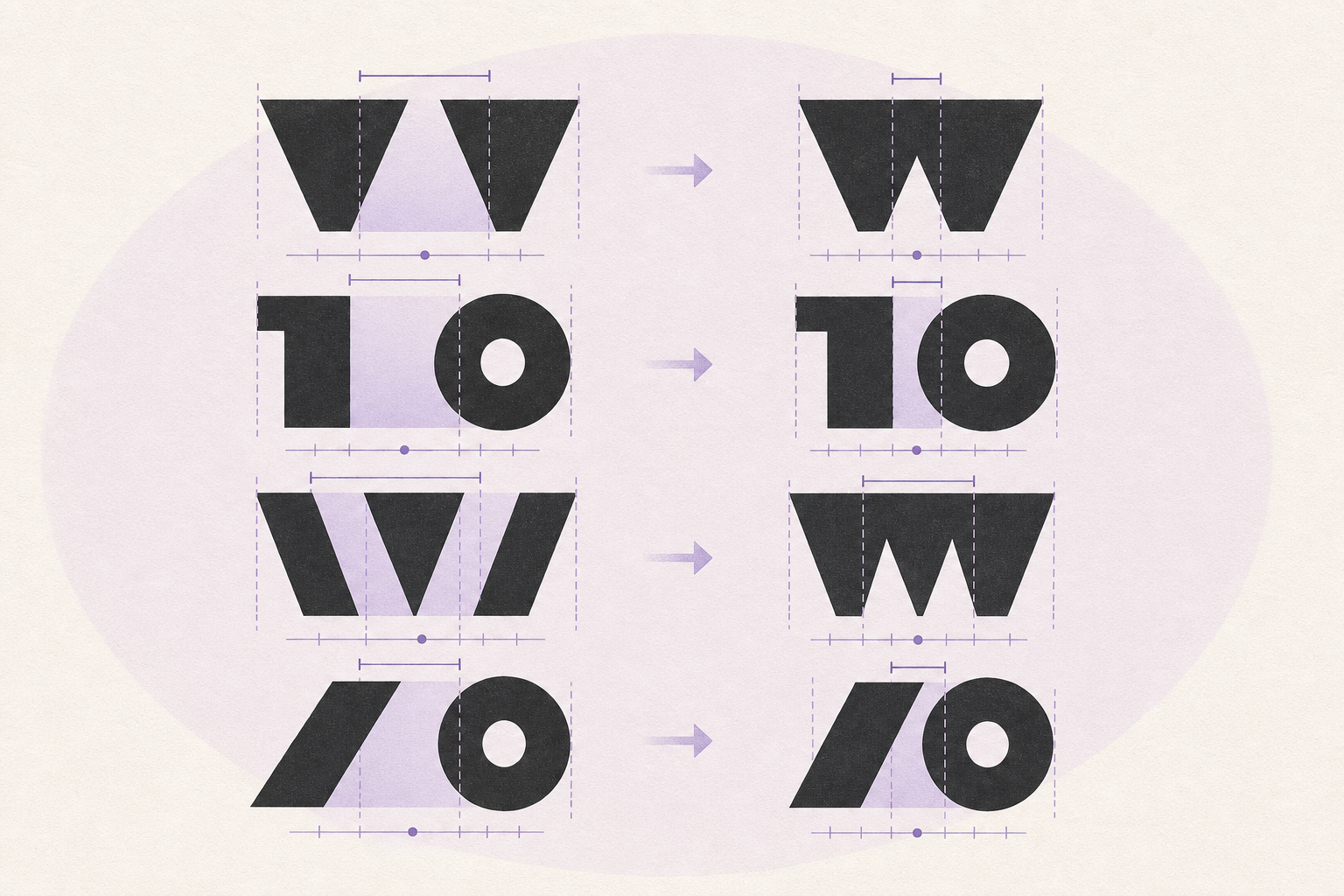
Кернинг — это настройка расстояния между конкретными парами букв, которая помогает визуально выровнять слово и сделать текст цельным. Он особенно заметен в логотипах, заголовках и крупных надписях, где даже небольшой дисбаланс меняет ритм композиции. Ниже разберём принципы кернинга, практические приёмы, ошибки и способы проверки.
Кернинг: простое определение термина
В типографике кернингом называют изменение бокового интервала между двумя определёнными символами. Цель не в том, чтобы сделать все буквы одинаково близкими, а в том, чтобы расстояния между их визуальными массами воспринимались равномерно. Поэтому кернинг часто выполняется не по геометрической линейке, а оптически — с учётом формы знаков.
Например, рядом стоящие латинские буквы A и V образуют заметное пустое пространство в верхней части пары, хотя их формальные границы могут находиться на одинаковом расстоянии. При корректировке V приближают к A, чтобы слово выглядело собранным. Аналогичная проблема возникает в парах To, Ta, Wa, Yo, AV и других сочетаниях с диагоналями, округлыми контурами или нависающими элементами.
Как кернинг отличается от трекинга и межбуквенного интервала
Кернинг работает локально: он меняет расстояние только между конкретными знаками. Трекинг, или общий межбуквенный интервал, применяется ко всему выделенному слову, строке или текстовому блоку. В настройках редактора эти параметры могут называться по-разному, но принцип остаётся тем же: кернинг исправляет отдельные проблемные пары, а трекинг меняет общий ритм набора.
- Кернинг — точечная настройка пары символов, например A и V.
- Трекинг — равномерное изменение интервала во всём фрагменте.
- Интерлиньяж — расстояние между строками, а не между буквами.
- Ширина начертания — характеристика самого шрифта, которую нельзя полностью заменить настройкой интервала.
- Выравнивание по ширине — распределение пробелов между словами и отдельная задача верстки.
Эти понятия важно не смешивать. Если слово в целом выглядит слишком плотным, сначала проверяют трекинг и выбранное начертание. Если почти весь набор гармоничен, но одна пара создаёт провал или столкновение, нужна именно кернинговая корректировка. Избыточное уменьшение общего интервала не исправит локальную проблему и может ухудшить читаемость.
Почему расстояние между буквами влияет на восприятие
Читатель воспринимает слово не как ряд независимых прямоугольников, а как цельную группу форм. Когда внутри группы появляются слишком большие пустоты, слово распадается на части. Когда соседние знаки почти соприкасаются, возникает ощущение тесноты и визуального шума. Кернинг поддерживает равномерный ритм, поэтому текст кажется аккуратным, устойчивым и профессионально набранным.
В крупном кегле эффект становится сильнее. На размере заголовка разница в несколько условных единиц заметна невооружённым глазом, потому что буквы занимают большую площадь и воспринимаются почти как графические объекты. В мелком основном тексте автоматический кернинг шрифта обычно достаточно эффективен, но качество зависит от гарнитуры, движка рендеринга, языка и конкретного сочетания символов.
Хороший кернинг редко замечают отдельно: читатель просто видит слово, в котором ничего не мешает чтению.
Какие пары букв чаще всего требуют настройки
Проблемные сочетания возникают там, где реальные контуры букв не совпадают с их прямоугольными метриками. Диагональные буквы создают клиновидные промежутки, округлые знаки оставляют оптические зазоры, а выступающие элементы могут визуально нависать над соседним символом. Поэтому дизайнер оценивает не только левую и правую границу глифа, но и плотность чёрных форм внутри пары.
- Диагональные пары: AV, VA, To, Ta, Te, Wa.
- Округлые пары: Oo, Oc, Co, Go и сочетания с C, O, G.
- Пары с узкими знаками: Ta, Ly, Ty, Fi.
- Сочетания с пунктуацией: кавычки, дефисы, точки и скобки.
- Кириллические пары: ЛА, ТА, ГА, УА, ТУ и другие комбинации, зависящие от рисунка гарнитуры.
В кириллице нельзя автоматически переносить правила с латиницы. У русских букв есть собственная пластика: Л, Д, Т, У, Ч и Я формируют характерные диагональные и нависающие элементы. Кроме того, кириллические и латинские знаки могут встречаться в одном слове или интерфейсе, например в названиях продуктов и технических обозначениях. Такие смешанные пары нужно проверять отдельно.
Автоматический и ручной кернинг в шрифтах
Современный шрифт может содержать таблицу кернинговых пар. Она хранит поправки для сочетаний символов и применяется программой при наборе текста. Такой подход удобен для распространённых комбинаций и снижает объём ручной работы. Однако автоматическая настройка не гарантирует идеальный результат в каждом логотипе: контекст, размер, соседние слова и особенности композиции могут потребовать дополнительной правки.
Ручной кернинг выполняют уже на уровне конкретного макета. Дизайнер может изменить расстояние между буквами в заголовке, знаке или короткой надписи, не меняя сам файл шрифта. Это особенно уместно для логотипов, обложек, упаковки, постеров и интерфейсных экранов с крупными заголовками. В длинном тексте ручные исправления обычно неэффективны: лучше выбрать подходящую гарнитуру и проверить её таблицу пар.
Короткий вывод
Кернинг — это не декоративная мелочь, а инструмент управления ритмом и целостностью текста. Он помогает сделать надпись аккуратной, улучшает восприятие заголовков и раскрывает качество шрифта в деталях. Используйте автоматическую настройку как основу, а заметные пары проверяйте вручную в реальном макете.